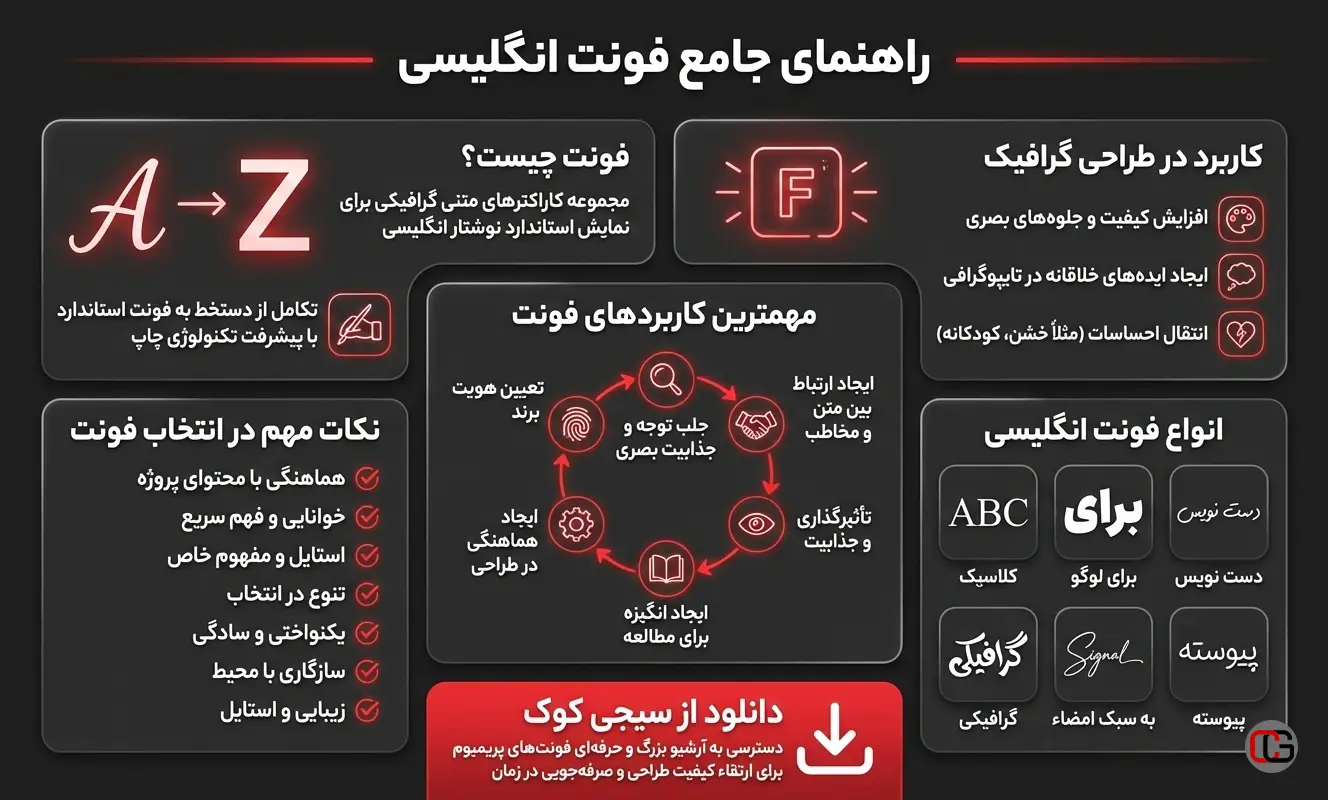
فونت انگلیسی چیست؟
فونت انگلیسی مجموعه ای از کارکتر های متنی به شکل گرافیکی هستند، که تصویر نوشتاری متون انگلیسی را به صورت استاندارد نمایش می دهند، در واقع فونت همان شکل ظاهری حروف هست و مشخص میکند نوشتار انگلیسی چگونه روی صفحه نمایان شود.
فونت چیست؟
فونت (Font) یک مجموعه از کاراکتر های متنی است، که به صورت گرافیک ایجاد شده اند و تصویر نوشتاری یک زبان، مثلا همین زبان انگلیسی را نمایش می دهند، و در واقع مشخص میکنند که شکل ظاهری یک زبان به چه صورت روی صفحه به نمایش در بیاید.
در زمان های قدیم که تکنولوژی به اندازه امروز پیشرفته نبود و تایپوگرافی به مفهوم امروزی وجود نداشت، افراد مجبور بودند با دست خط خود مطالب را نوشته و همین امر باعث میشد متن های نوشته شده برای هر فرد شکل متفاوتی داشته باشد و در بعضی موارد مردم را دچار مشکل میکرد و حتی نمی توانستند متن را به درستی بخوانند.
امروزه با گسترش صنعت چاپ و پیشرفت تکنولوژی مشکل ناخوانای متن ها حل شد، و امروزه مهم نیست چه کسی با چه دست خطی، یک متن را می نویسد، تمامی متون، مطالب و مقالات مورد نظر با یک خروجی یکسان تحت یک استاندارد خاص که به آن فونت می گویند، نمایش داده شده و یا چاپ می شوند.
کاربرد فونت انگلیسی در طراحی گرافیک
یکی از مهمترین بخش ها در هر طراحی گرافیکی تایپوگرافی و ظاهر متن در آن پروژه طراحی است، به همین دلیل طراحان گرافیک در هر زمینه ای به آرشیوی بزرگ و متنوع از FONT های عمومی و گرافیکی برای انتقال مفاهیم متنی خود نیاز دارند.
فونت های مختلف جلوه های خاصی را به طراحی های گرافیک القا میکنند و باعث افزایش کیفیت نتیجه نهایی یک طراحی گرافیکی میشوند. همچنین استفاده خلاقانه طراحان از فونت های مختلف و ویرایش آن ها باعث ایجاد بی نهایت ایده های خلاقانه در ارائه تایپوگرافی در طراحی های میشوند.
فونت بخش مهمی از هر طراحی گرافیکی است، طراحان می توانند با استفاده از فونت احساس یک متن و یک کار گرافیکی را به کاربر انتقال می دهند، یک فونت با ظاهر خشن و لبه های تیز می تواند حس خشونت را انتقال دهد، یک فونت با رنگ های متنوع و شکلی فانتزی می تواند یک حس کودکانه را انتقال دهد و هزاران مثال دیگر…
مهمترین کاربرد های فونت ها
- جلب توجه و ایجاد جذابیت: فونت های مناسب در پروژه ها با موضوعات مختلف می توانند با عث ایجاد توجه در مخاطب و یا ایجاد جذابیت بصری شوند.
- ایجاد ارتباط بین متن و مخاطب: فونت مناسب نقش اساسی و مهمی در ایجاد ارتباط بین متن و مخاطب دارد و می تواند مخاطب را به خواند و درک مطلب دعوت کند، همچنین از متن برای ایجاد احساسات و انگیزه های متنوع در مخاطب استفاده می شود.
- تاثیر گذازی و جذابیت بصری: برخی فونت ها دارای استایل ها و تأثیرات ویژه ای هستند که می توانند به طراحی جذابیت بیشتری ببخشند.
- ایجاد انگیزه برای مطالعه و فهم متن: فونت ها می توانند بر سرعت و راحتی مطالعه متن تأثیر بگذارند و به درک بهتر مطلب کمک کنند.
- ایجاد هماهنگی و یکدستی در طراحی: انتخاب فونت مناسب می تواند به ایجاد هماهنگی و یکنواختی در طراحی متن و مواد چاپی کمک کند.
- تعیین هویت برند: فونت ها به عنوان یکی از عوامل اصلی در تعیین هویت برند مورد استفاده قرار می گیرند و می توانند شناخت برند را تقویت کنند.
جادوی فونت ها در ویدیو؛ از جلب توجه تا درگیر کردن احساسات
راستش را بخواهید، تدوین ویدیو فقط بریدن و چسباندن و کنار هم گذاشتن کلیپ ها نیست. وقتی از یک فونت انگلیسی مناسب در تایتل ها استفاده می کنید، ناخود آگاه توجه مخاطب را روی پیام خودتان میخکوب می کنید. مثلاً وقتی دارید با یک پروژه آماده افترافکت کار میکنید و فقط قصد دارید محتوای متنی پروژه را تغییر دهید، یک فونت ضخیم و جذاب می تواند کل حس و حال پروژه را تغییر دهد، همین برای ساخت موشن گرافیک حرفه ای هم صدق میکند.
یکی دیگر از کاربرد های مهم فونت های انگلیسی، انتخاب فونت درست برای زیرنویس یا تیتراژ در پروژه های تدوین با پریمیر است که ارتباط عمیق تری بین تصویر و بیننده ایجاد کنید، حتی اگر از پروژه آماده پریمیر هم استفاده می کنید، که در آن همه چیز از قبل طراحی شده است، بهتر است فونت ها را متناسب با سلیقه و هدف ویدیو خودتان تغییر دهید.
هویت برند شما با یک فونت انگلیسی شکل میگیرد
فونت ها یکی از اصلی ترین پایه های هویت بصری برای هر کسب و کاری هستند و اصلاً نباید دست کم گرفته شوند. وقتی برای طراحی هویت یک برند جدید، از لوگو آماده استفاده می کنید یا حتی خودتان آن را طراحی کنید، اولین چیزی که شخصیت و کلاس کاری آن لوگو را نشان میدهد، تایپوگرافی آن است. علاوه بر این فونت ها در تمامی بخش های هویت برند، از سربرگ ها، کارت ویزیت ها، ست های اداری گرفته تا حتی موکاپ های که شما برای ارائه ایده خود استفاده میکنید کاربرد دارند.
طراحی برای شبکه های اجتماعی؛ جایی که فونت ها حرف اول را میزنند
در فضای شلوغی مثل اینستاگرام که همه با سرعت در حال اسکرول کردن هستند، چطور مخاطب را متوقف کنیم تا محتوای ما را ببیند؟ جواب ساده است: جذابیت بصری سریع. استفاده از یک قالب آماده اینستاگرام به تنهایی کافی نیست؛ بلکه آن فونت انگلیسی که برای تیتر کاور انتخاب میکنید، همان قلابی است که چشم مخاطب را درگیر میکند. برخی فونت ها استایل های ویژه ای دارند که در طراحی پست و استوری معجزه میکنند و باعث میشوند صفحه شما در میان هزاران محتوای دیگر، کاملاً یکدست و حرفه ای به نظر برسد.
فونت های یکی از موارد ضروری و پیش نیاز برای شروع هر طراحی گرافیکی است، همچنین تنوع بالا در FONT ها باعث میشود طراحان با دست باز تر ایده های متنوع را خلق کنند. دسترسی به آرشیو بزرگ و متنوع از فونت های حرفه ای و استاندارد میتواند تا حد زیادی کیفیت طراحی نهایی را ارتقا دهند و در صرف زمان و هزینه های برای یک پروژه صرفه جویی کند.